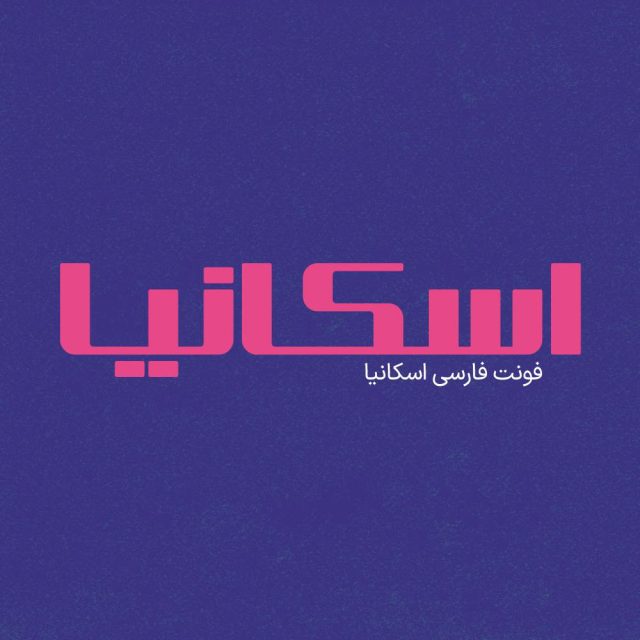
فونت فارسی اسکانیا Scania Font
فونت فارسی اسکانیا شخصیت کاریزماتیک خود را با تعادل منصفانه‌ای که بین شکل انسانی حروف و جنبه هندسی آن ترکیب کرده به دست می‌آورد. فونت اسکانیا…
فونت فارسی اسکانیا شخصیت کاریزماتیک خود را با تعادل منصفانه‌ای که بین شکل انسانی حروف و جنبه هندسی آن ترکیب کرده به دست می‌آورد. فونت اسکانیا از طریق حروف و چشم‌های بزرگ نفس می‌کشد و با هدف اینکه می‌خواهد به جای خواندن، ابتدا دیده شود طراحی شده است. فونت زیبای اسکانیا بهترین گزینه برای استفاده در تیتر روزنامه‌ها، مجلات و کتاب‌ها است.
فونت فارسی اسکانیا یک فونت تک وزن با کاربرد طراحی لوگوتایپ و طراحی های مختلف همچون کتاب و تولید محتوای متن های کوتاه و عناوین می باشد. این فونت با ساختار حروف خود مناسب استفاده در لوگوهای نوشتاری می باشد. همچنین از این فونت در طراحی تابلوهای چلنیوم هم به دلیل ساختار منحصر به فردش می توانید استفاده کنید. در ادامه برای شما نمونه تایپ های این محصول حرفه ای رو آماده کردیم که میتونید مشاهده کنید.
• مناسب طراحی بسته بندی ها و چاپ
• فونت ویژه تبلیغات محیطی
• فونت طراحی کاور اینستاگرام
• فونت حرفه ای برای تولید محتوا
• فونت فارسی طراحی وبسایت
• فونت طراحی لوگو تایپ فارسی
• مناسب استفاده در تابلو های چلنیوم و طراحی حروف
پیشنمایش و نمونه تایپ های فونت اسکانیا